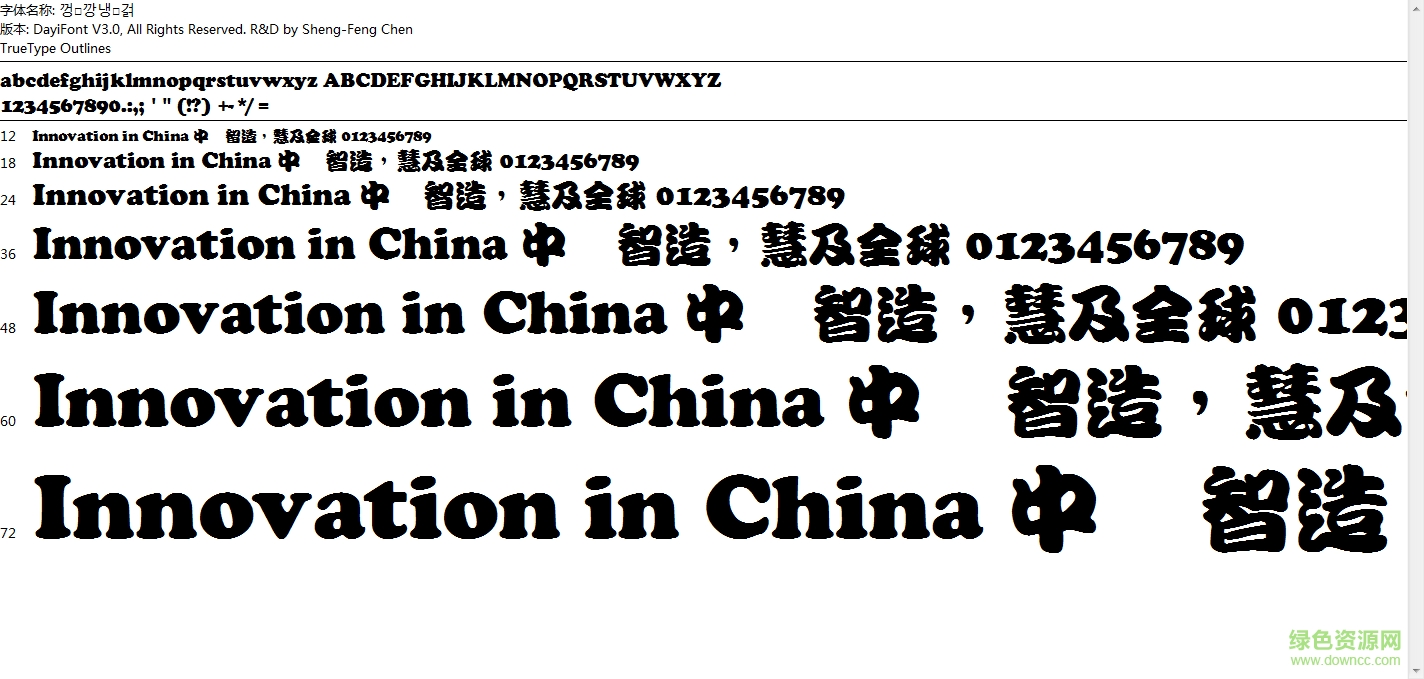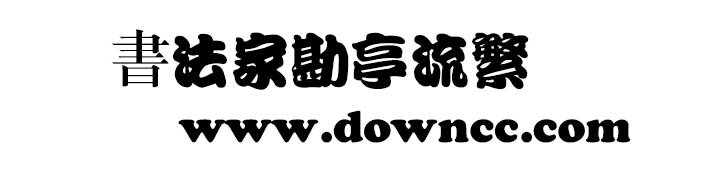
書法家勘亭流字體繁體是一款非常美觀的字體,采用了繁體書法,字型柔和,端莊大方,廣泛的應(yīng)用于平面設(shè)計、廣告設(shè)計、印刷包裝等領(lǐng)域,歡迎來綠色資源網(wǎng)下載體驗!
勘亭流體筆畫粗,字形圓潤、敦厚,筆畫中極少出現(xiàn)直線與折角,幾乎全由曲線和彎角
勘亭流體構(gòu)成,形成了其特有的藝術(shù)效果,被廣泛應(yīng)用于表現(xiàn)日式風(fēng)格的招牌、標(biāo)題、包裝等上面,倍受廣大平面設(shè)計者的青睞。